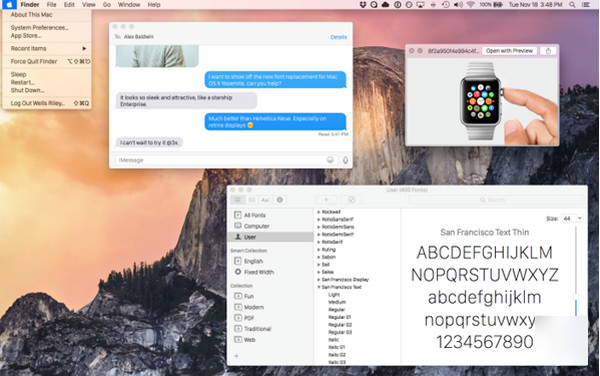
San Francisco字體這是蘋果在十一月份專為 Apple Watch 推出的全新的字體,蘋果表示San Francisco字體進(jìn)行了全新的設(shè)計(jì),在Apple Watch上更好用,同時(shí) Mac OS 系統(tǒng)用戶們也可以下載過來試試哦!
基本簡(jiǎn)介
蘋果官方稱為了提升Apple Watch的易讀性對(duì)系統(tǒng)字體進(jìn)行了重新設(shè)計(jì)。在大尺寸版本中,每個(gè)字母之間間距會(huì)進(jìn)行輕微的壓縮,以充分利用屏幕空間。但是在小尺寸版本中,每個(gè)字母的間距將會(huì)進(jìn)行放大,尤其是“a”或者“e”等字母將會(huì)顯得更大,這樣確保在第一眼中不會(huì)產(chǎn)生差錯(cuò)。